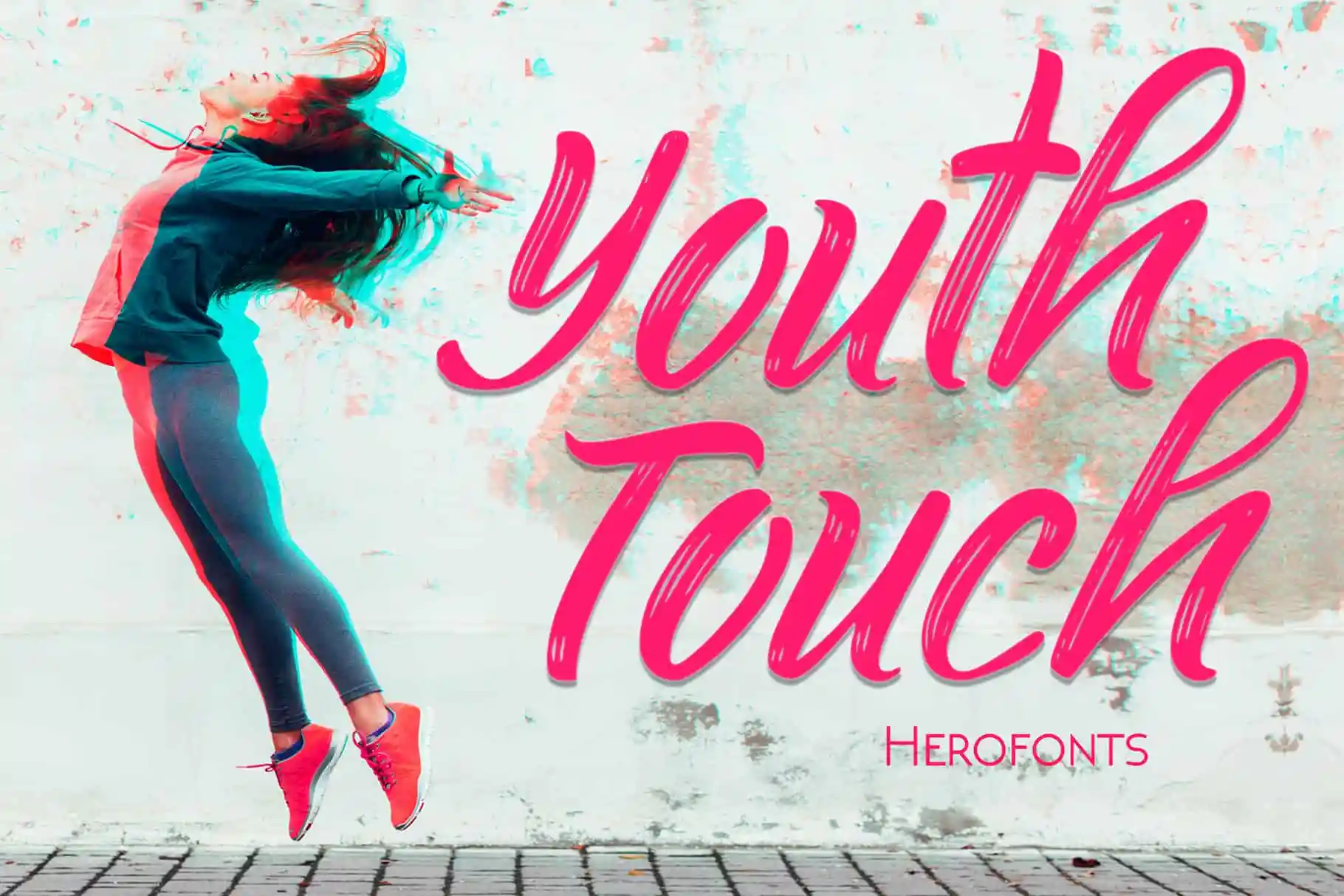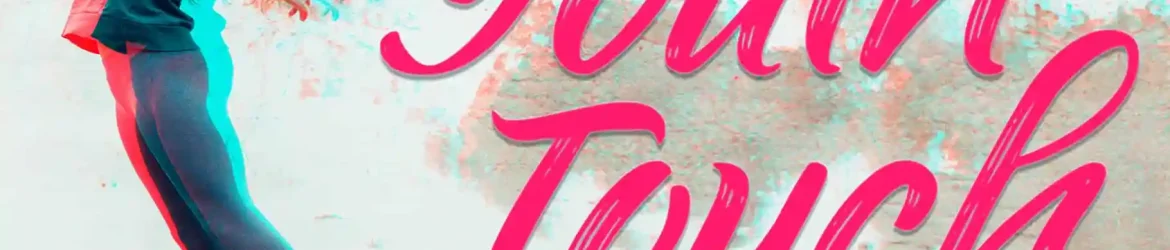
Youth Touch © Typeface – Download Grátis
A Young Touch Typefont é uma atraente escolha para designers que procuram harmonia tipográfica, ideal para uma variedade de projetos. Este tipo de letra Brush foi criado com designers, criadores de logotipos e marcas, noivas, postagem de mídia social, anúncios, embalagens de produtos e revistas em mente. Essa fonte Brush oferece um toque jovial e vibrante que combina perfeitamente para qualquer projeto, tornando-a uma opção ótima tanto para iniciantes quanto para designers mais experientes. Com Young Touch, você ganha a liberdade de criar designs que expressam sua personalidade com elegância e estilo moderno.